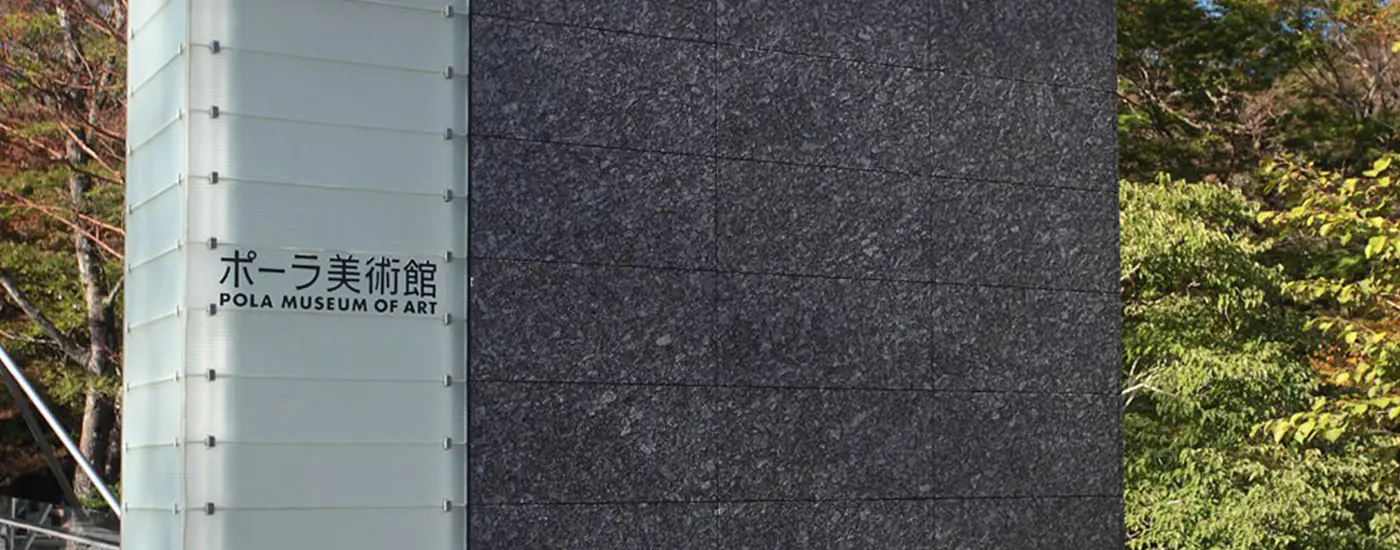
空間に寄り添う、静謐な文字
ポーラ美術館
副館長 碓井 健司氏
神奈川県箱根仙石原にあるポーラ美術館の設立は2002年。その9500点にもおよぶコレクションは19世紀のフランス印象派やエコール・ド・パリなどの西洋絵画に加え、日本人画家による洋画や日本画さらには東洋陶磁やガラス工芸、化粧道具までと豊富な収蔵で知られています。建築のコンセプトは「箱根の自然と美術の共生」。富士伊豆箱根国立公園内の約12万平方メートルの敷地には樹齢300年を超える巨大なブナ林、滑らかな美しい木肌を持つヒメシャラの樹林など、緑豊かな自然が広がっています。この自然環境を保護するため建物の大部分を地中に埋め込み、貴重な自然景観の保存に最大限配慮した設計となっています。また、世界的名品と出会う展示室の光ファイバー照明、幻想的なロビーの光壁や東洋初の完全免震構造など多くの革新的な技術を採用。自然の光を感じる透明感のある美しい美術館として高く評価され、日本建築学会賞と村野藤吾賞を受賞しています。
ポーラ美術館開館準備当時、美術館サイン計画を担当したポーラ化成工業株式会社 デザイン研究所の碓井健司氏(現ポーラ美術館 副館長)は、「最初に館名である『ポーラ美術館』のロゴタイプに取り組みました。本格的な美術館らしさを感じさせる、静謐で上質なものにしたかったのです。収蔵西洋絵画に関しては印象派の作品が多いこと、建築に関しては自然の光を意識した造りになっていることから、光のイメージを盛り込みたいと思っていました。」と述べています。
タイププロジェクトは、ポジおよびネガで使用するケースを想定してポーラ美術館のロゴタイプを制作しました。反転しても同じ印象であることを検証し、さらに縦組みと横組みの文字間や行間のバランスを細かく調整しています。
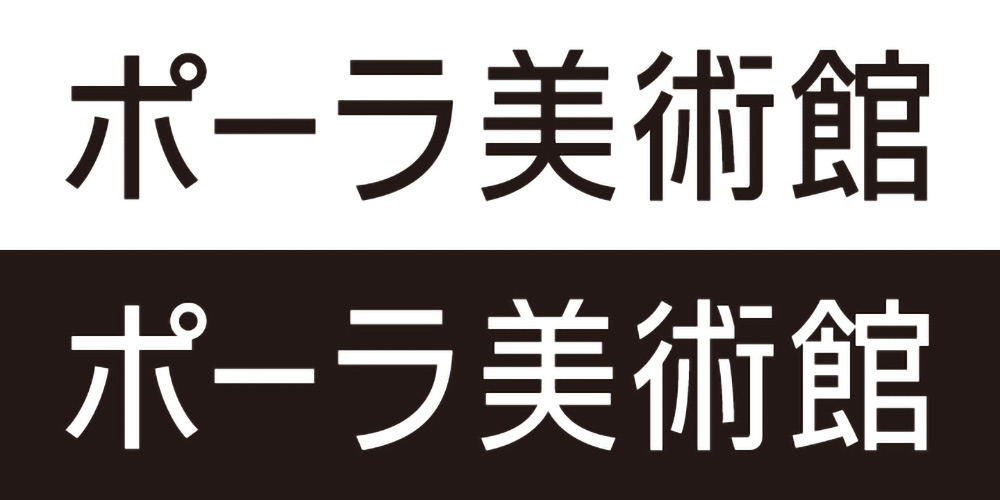
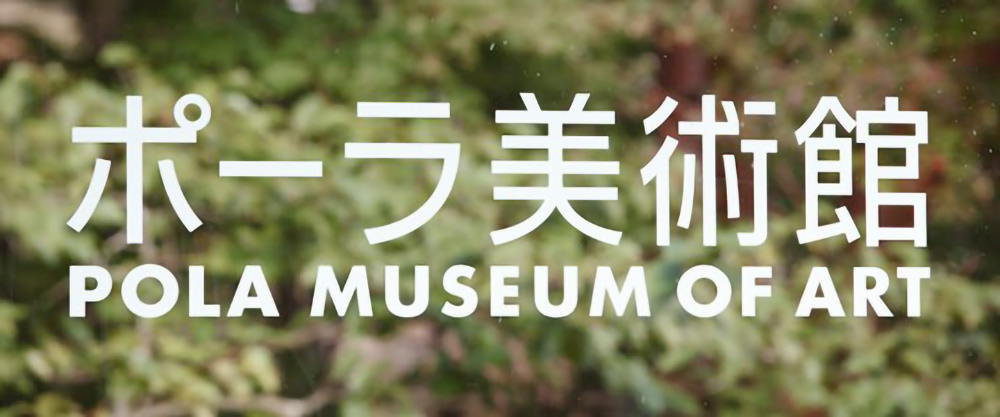
「文字は水や空気みたいなもの。だからこそ普遍的な存在としてこだわる必要があります。美術館の空間にこだわるのであれば、そこに表記する文字にもこだわらないと意味がありません。そうした流れで、ロゴタイプだけでなくポーラ美術館専用のサイン書体を創りたいと考えました。」
こだわりのある建物に合う凜とした上質な文字、という要望を受けタイププロジェクトが制作したのはポーラ美術館の案内表示に必要な84文字。先に施行が進んでいた縦長のサインボードとスリムなピクトグラムとの相性を考え、また伸びやかな空間構造を書体に反映させるため95%の長体で設計を行っています。自然な光を採り入れた美術館に文字をなじませるため画線を細めにした、明るく控えめなサイン用書体です。
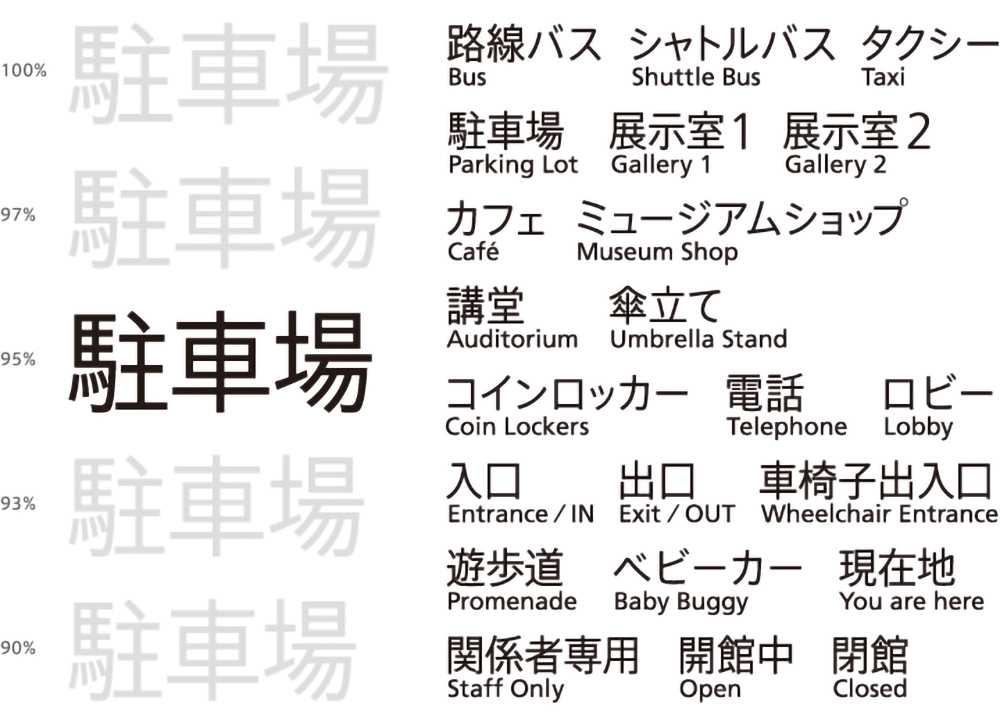
デザインが先行していたスリムな案内表示板と長体90%の美術館ロゴから、サイン用書体を長体でつくるというアイデアは自然に導かれた。正体、長体の97%、95%、93%そして90%を選択肢として提案し、95%の長体をベースにする案が採用された。文字の太さは、ふんだんに光を採りいれた美術館に寄り添うようわずかに「細み」と「明るさ」を感じるウエイトに設定した。
完成したポーラ美術館サイン専用書体(右)
サイン用に制作した文字数は、漢字48文字とひらがな4文字、カタカナ32文字の計84文字。欧文にはFrutigerを使用している。これとは別に、「定員、積載、開閉、用途、乗用、荷物用」などの文字をエレベータ用に正体バージョンで作り起こした。これらは文字サイズが小さくつぶれやすい漢字が多いため、サイン専用書体よりやや細いウエイトで作成した。
「ロゴタイプやサイン計画における文字間や行間というものは、建築における空間表現と同じだと気がつきました。美術館そのものが光にあふれた空間を目指していましたから、建築の考え方と文字の考え方が見事に呼応している。これは、私自身にとっても、大きな刺激になりました。ポーラ美術館専用サイン書体は華奢だけど凜として、みごとに調和しています。まさしく美術館のためにあるバランスを持つ、ミュージアム フォントの誕生です。」